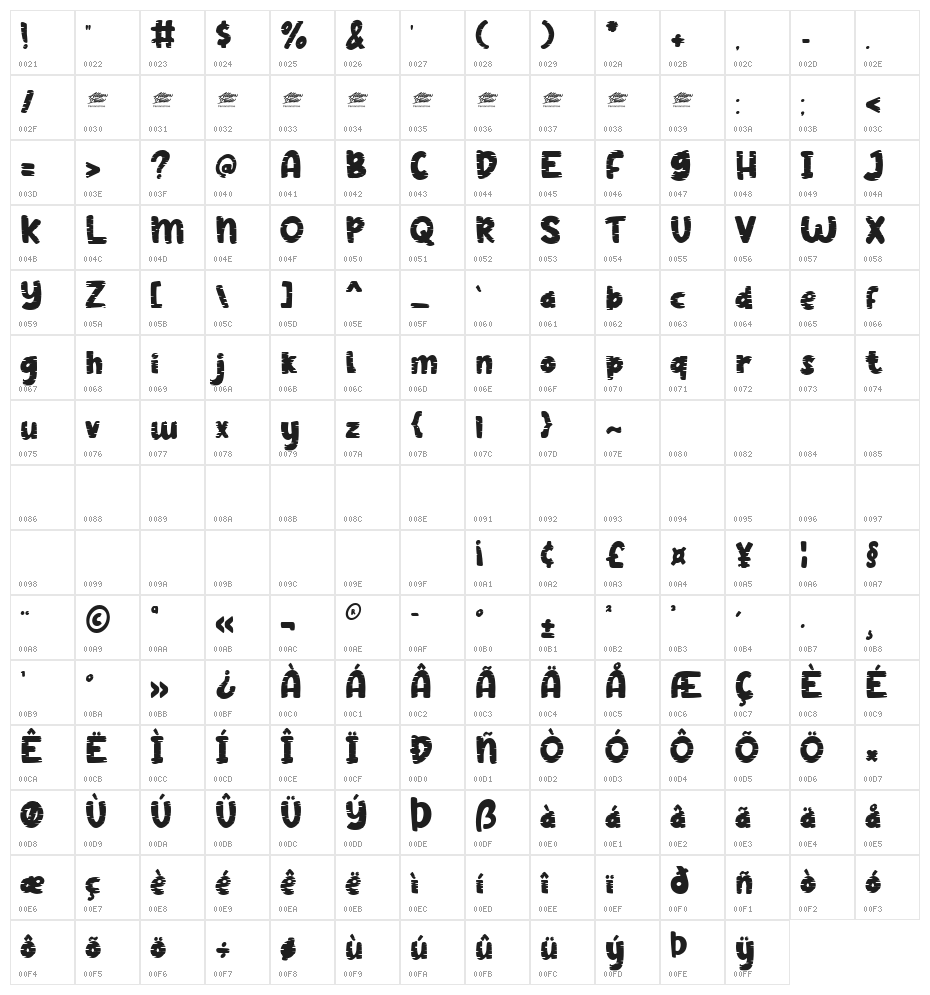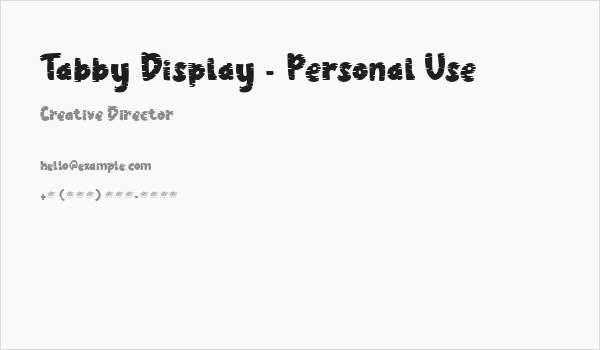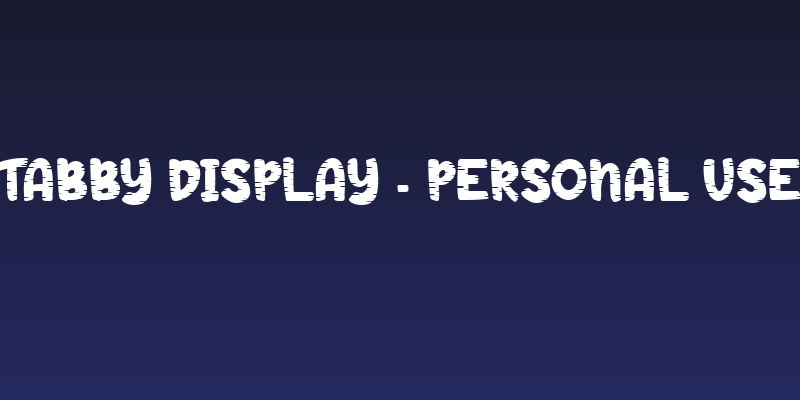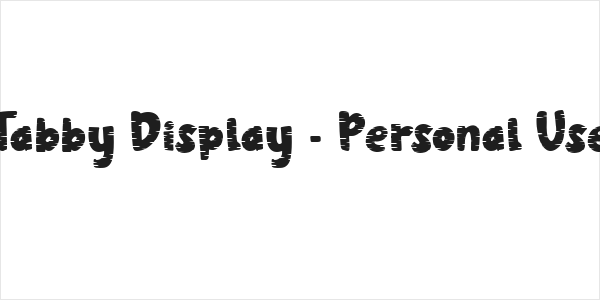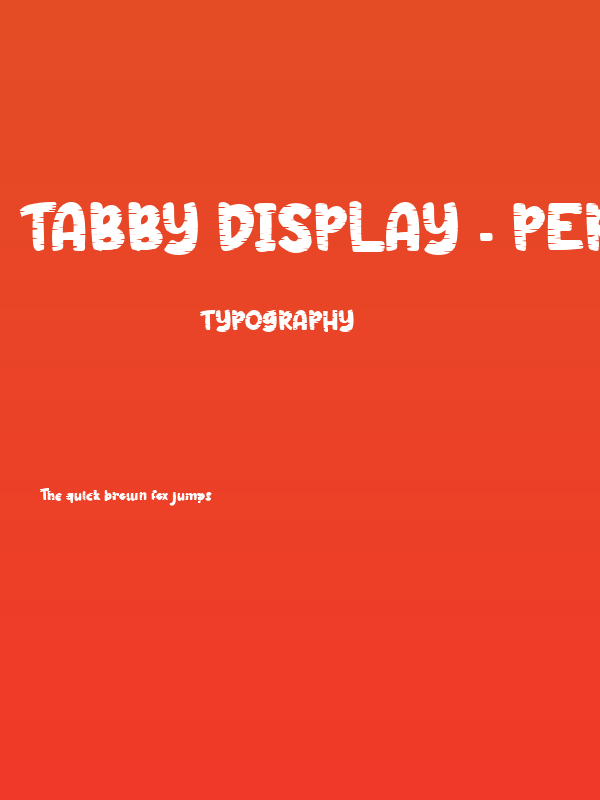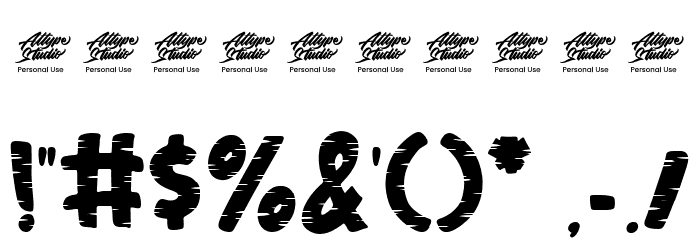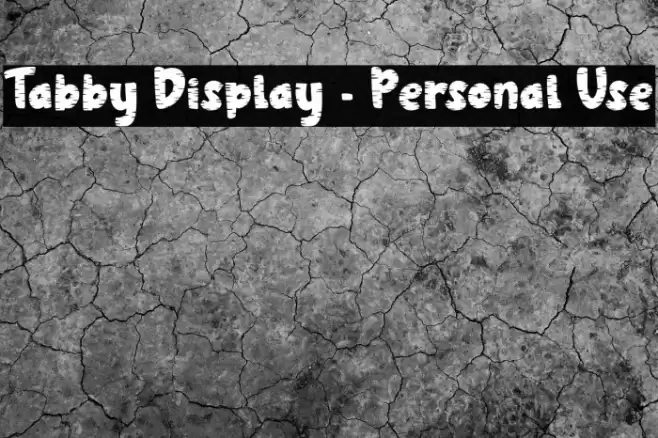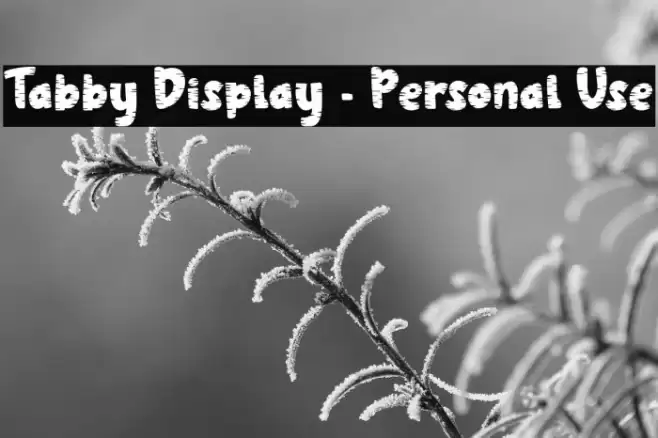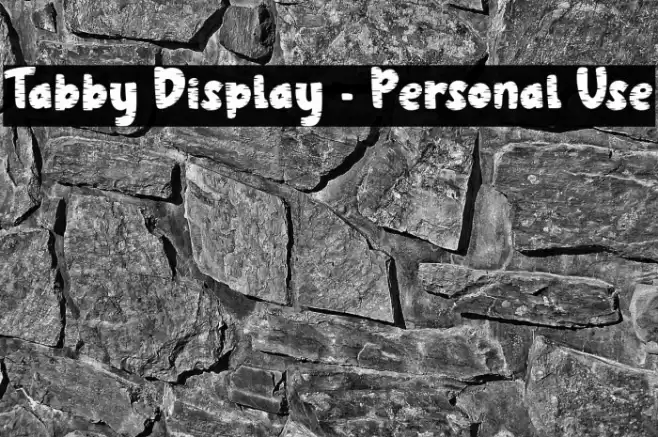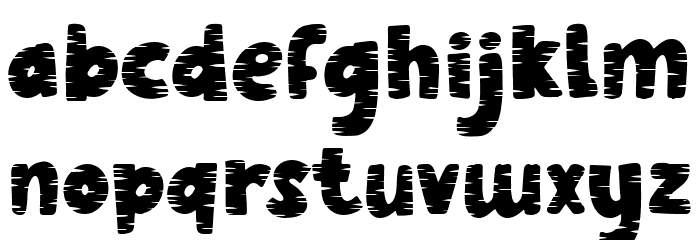
Tabby Display - Personal Use Font
✎ Cartoon
| カテゴリ | Cartoon |
| 全体的なスタイル | Playful, Energetic, Hand-drawn |
| おすすめプロジェクト | Ideal for posters, children's book covers, playful branding, and creative social media graphics. |